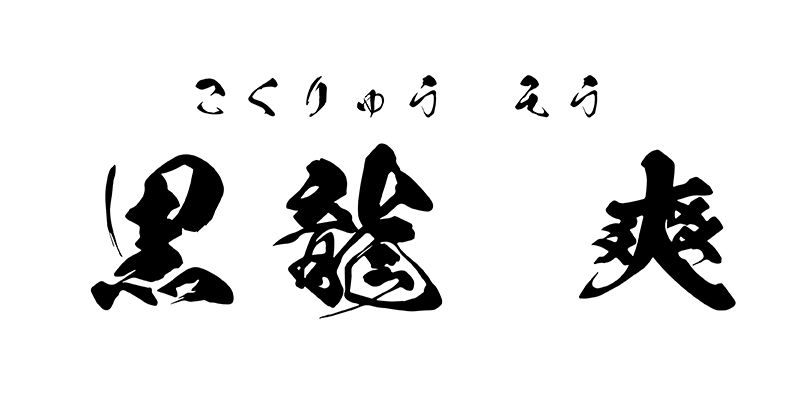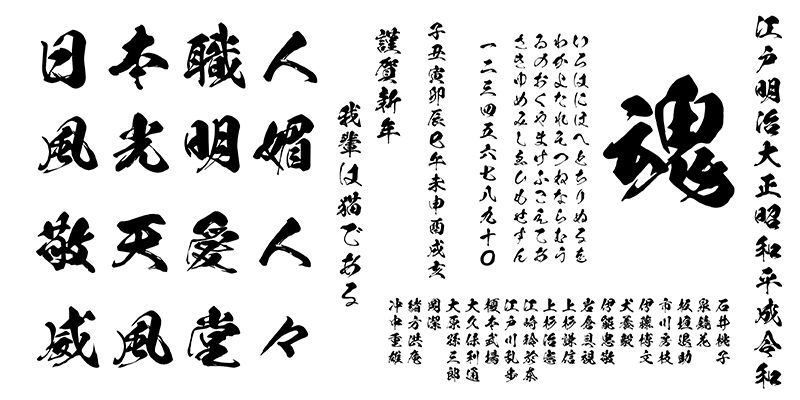
「黒龍」は、牡の龍が暗雲立ち込める空を荒々しく漂うさまをイメージして作られた筆書系デザイン書体です。太い線と細い線が入り混じる緩急のついた画線は、まるで猛々しい龍の感情の抑揚を表わしているかのようです。正方形を意識しすぎることなく、ダイナミックに描かれた 1 つ 1 つの文字は、一見、アンバランスにも見えますが、文章として組むとその力強いイメージで見事に調和します。 今回 Adobe Fonts に収録される「黒龍爽」は黒龍のカスレを少なくして容量を抑え、カッティングやアニメーション、ビデオクリップにも使いやすくなっています。